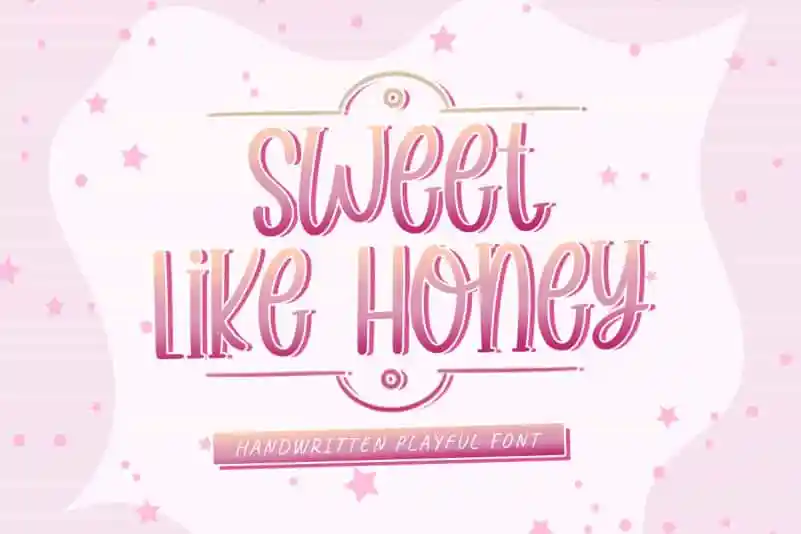
Sweet Like Honey Display Font – Download Grátis
A fonte “Sweet Like Honey Display Font” é uma elegante mistura de serif e sans-serif que desperta instantaneamente a memória nostálgica dos doces primaveristas, especialmente aqueles inofensivos mas cativantes que são como um beijo leve. Suavemente envolvente, esta fonte tem uma aparência encantadora e perfeita para diversas tarefas de design, seja para criar cartões de agradecimento, embalagens de produtos gourmet ou até mesmo para adicionar algum charme ao seu site. A inspiração na melena suave é notável, mas também há um toque versátil que faz deste uma opção ideal tanto para trabalhos formais quanto para um design casual e descontraído.